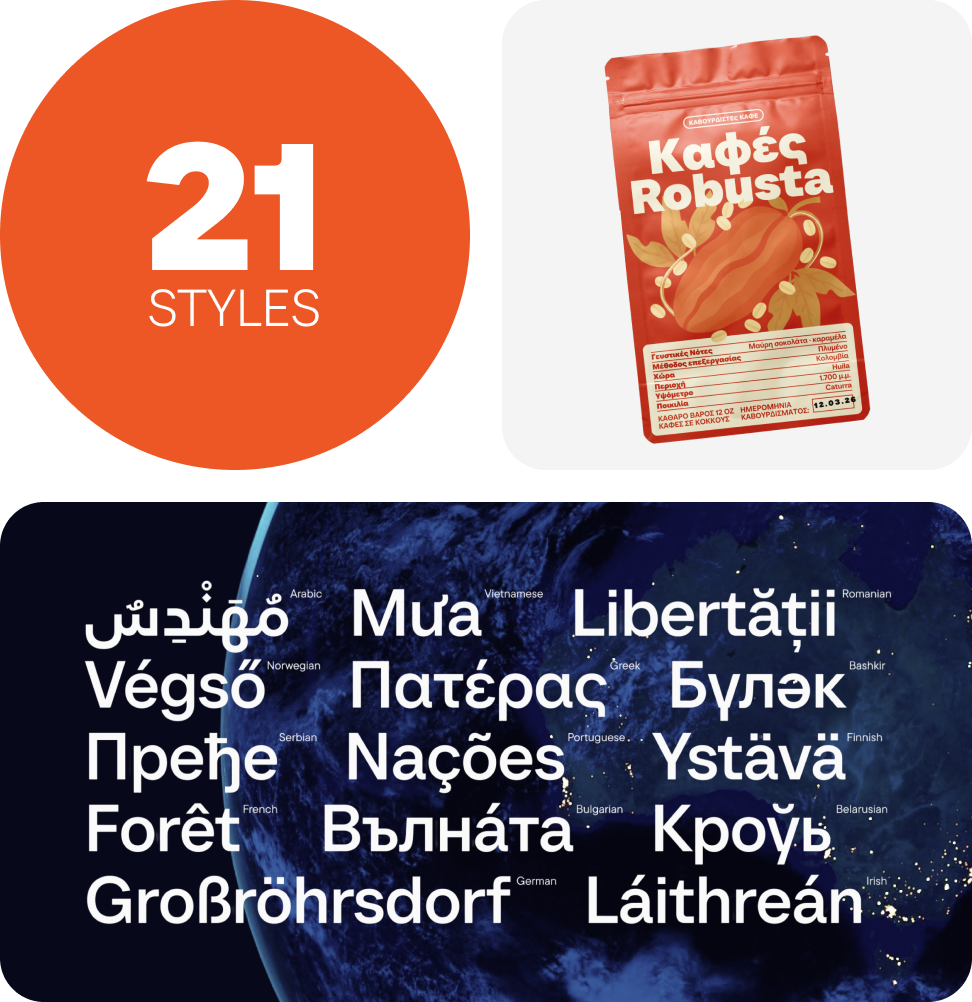
Große Schriftarten
TT Nooks Script besitzt eine eigenständige Zeichnung, für die es kaum direkte Vergleichspunkte gibt.
TT Supermolot Neue ist eine neu gestaltete, erweiterte und deutlich verbesserte Reinkarnation der beliebten Schriftfamilie.
TT Severs ist eine geometrische Sans Serif mit betonten inneren Rundungsübergängen. Das wichtigste visuelle Merkmal von TT Severs ist die ungewöhnliche Form der inneren Ovale.
TT Regins ist eine moderne schottische Serifenschrift. Starker Kontrast und scharfe dreieckige Serifen verleihen ihr einen strengen und kraftvollen Charakter, während raffinierte Formen, vergrößerte Kleinbuchstaben und leicht kondensierte statische Proportionen dem Design Eleganz verleihen.
TT Modernoir ist eine Display-Sans-Serif mit dynamischen Proportionen. Fließende Linien und feine Jugendstilformen verschmelzen in dieser Schrift harmonisch mit dem rhythmischen Fluss und der improvisatorischen Freiheit des Jazz.
TT Moons ist eine schlanke kontrastreiche Serifenschrift. Diese Schriftfamilie funktioniert besonders gut in klassischen Designkonzepten. TT Moons gehört zur Ästhetik moderner Glyptal-Schriften.
TT Disruptors ist eine flexible handgezeichnete Marker-Schrift. Ihr Design ist einzigartig: abgenutzte Kanten, variierende Strichstärken sowie verlängerte Ober- und Unterlängen verleihen ihr eine lebendige, dynamische Textur und handwerkliche Ausstrahlung. Der Charakter dieser Schrift ist temperamentvoll und emotional, zugleich aber warm und voller Seele.
TT Interphases Pro ist eine Neo-Grotesk-Sans-Serif mit gleichbreiten Proportionen.
TT Biersal ist eine Display-Sans-Serif mit freigeistigem, verspieltem und abenteuerlustigem Charakter. Das Konzept dieser Schrift wurde von einem deutschen Plakat aus den frühen 1930er-Jahren inspiriert.
TT Cometus ist eine ausdrucksstarke Schrift, die vom ersten Moment an fesselt.
TT Espina ist eine Display-Antiqua mit ausdrucksstarken Serifen.
TT Norms® Pro ist eine typografische Legende, die von weltbekannten Marken geschätzt wird. Entwickelt durch mehrere Iterationen, hat sie MyFonts erobert und typografische Vielseitigkeit neu definiert. Ein Design-Arbeitspferd, das sich von einem bescheidenen Werkzeug in einen unverzichtbaren kreativen Begleiter verwandelt.
TT Commons™ Pro ist das typografische Kraftpaket des Studios. Eine Schriftart, die so vielseitig ist, dass sie sich einer Kategorisierung entzieht und Stil und Funktion nahtlos verbindet. Für Designer, die eine universelle Grundlage suchen, die jedes Projekt aufwertet, ist dies die endgültige Wahl.
TT Hoves Pro ist eine skandinavische serifenlose Schrift, die minimalistische Eleganz versprüht. Sie ist die Geheimwaffe eines Designers, der komplexe Herausforderungen mit müheloser Präzision in visuelle Poesie umwandelt, und dabei gleichzeitig dezent und unverwechselbar.
TT Supermolot Neue verändert die visuelle Kommunikation grundlegend! Eine fortschrittliche, modulare serifenlose Schrift, die den Puls der technologischen Innovation einfängt und eine elektrisierende Vision für alles von immersiven Spieloberflächen bis hin zu kühnen visuellen Erzählungen bietet.
TT Firs Neue ist eine ausgewogene serifenlose Schrift, die von der skandinavischen Designphilosophie geprägt ist. Elegant und vielseitig, poliert durch zwei bewusste Überarbeitungen, um typografische Perfektion zu erreichen.
TT Rounds Neue ist eine weiche und freundliche Schrift, die es versteht, anders zu sein. In leichteren Schriftschnitten wirkt sie minimalistisch und neutral. In den fetten Schriftschnitten bläht sie sich auf und erreicht maximale Rundheit, die kindlichen Charme ausstrahlt.
TT Fors ist ein Schweizer Taschenmesser der Typografie. Diese geometrische serifenlose Schrift ist durch ihre klaren, raffinierten Proportionen vielseitig einsetzbar. Sie kann zur Definition von Schnittstellen oder zur Gestaltung von visuellen Akzenten verwendet werden.
TT Ramillas ist eine stilvolle und moderne Serifenschrift, die Design zu einer Kunstform erhebt. Sie zeichnet sich durch ihre einzigartigen dekorativen Stile und Initialen mit floralem Ornament aus und schafft visuelle Erlebnisse, die wirklich einmalig sind. Die mit dem Modern Cyrillic Award ausgezeichnete Schrift, die bereits über 3000 Websites weltweit ziert, definiert typografische Raffinesse neu.
TT Berlinerins ist eine Grotesk, inspiriert von Holzlettern auf Plakaten aus dem ersten Drittel des 20. Jahrhunderts, und bringt die historische Komponente Berlins zum Ausdruck.
TT Bells verbindet die elegante Weichheit einer Antiqua mit einem komplexen und mutigen Temperament, das sich in geraden Strichabschlüssen und pfeilförmigen Serifen zeigt. Die Schrift basiert auf der Breitfeder, die diese charakteristischen Abschlüsse und Serifen erzeugt.